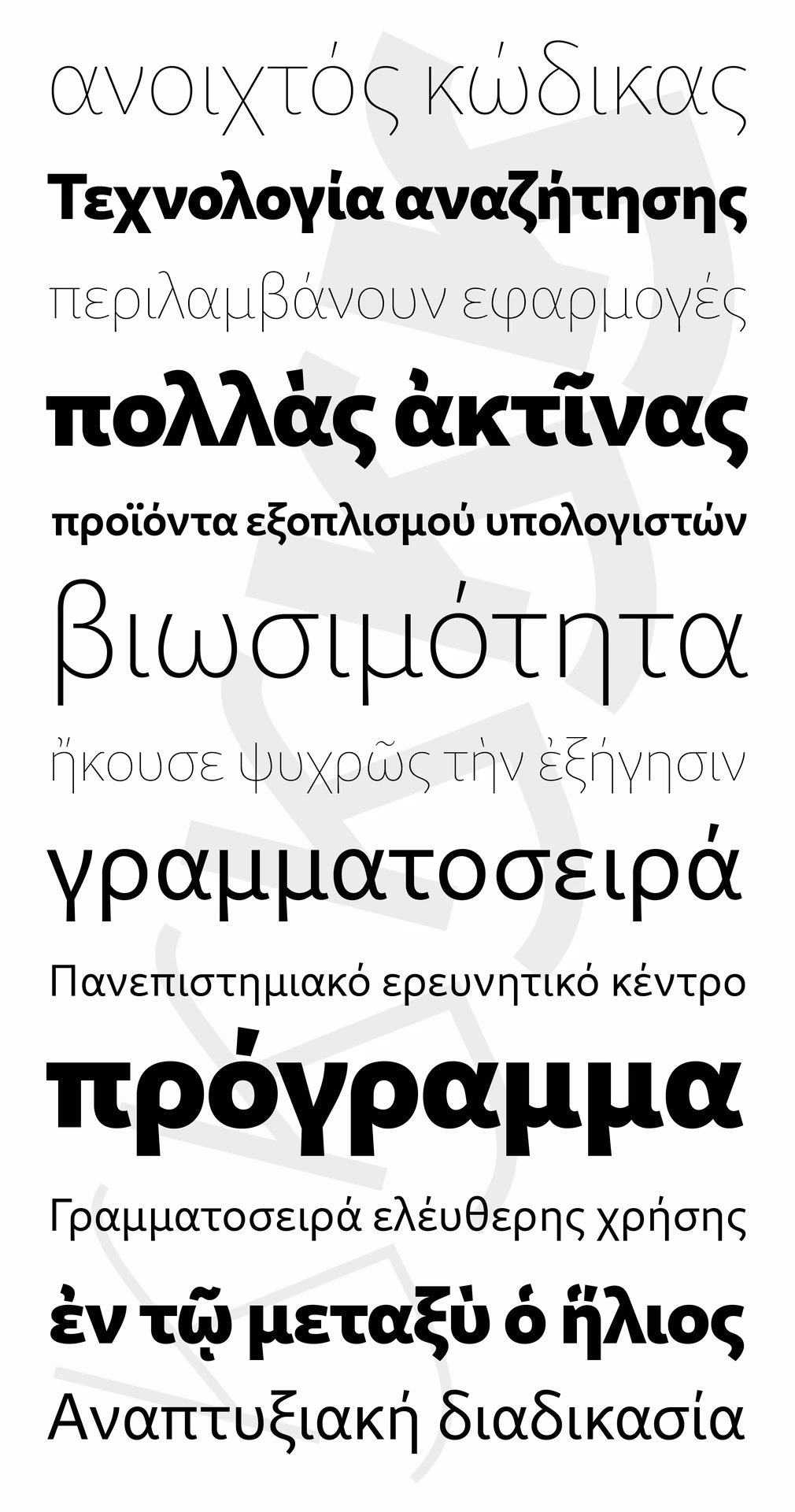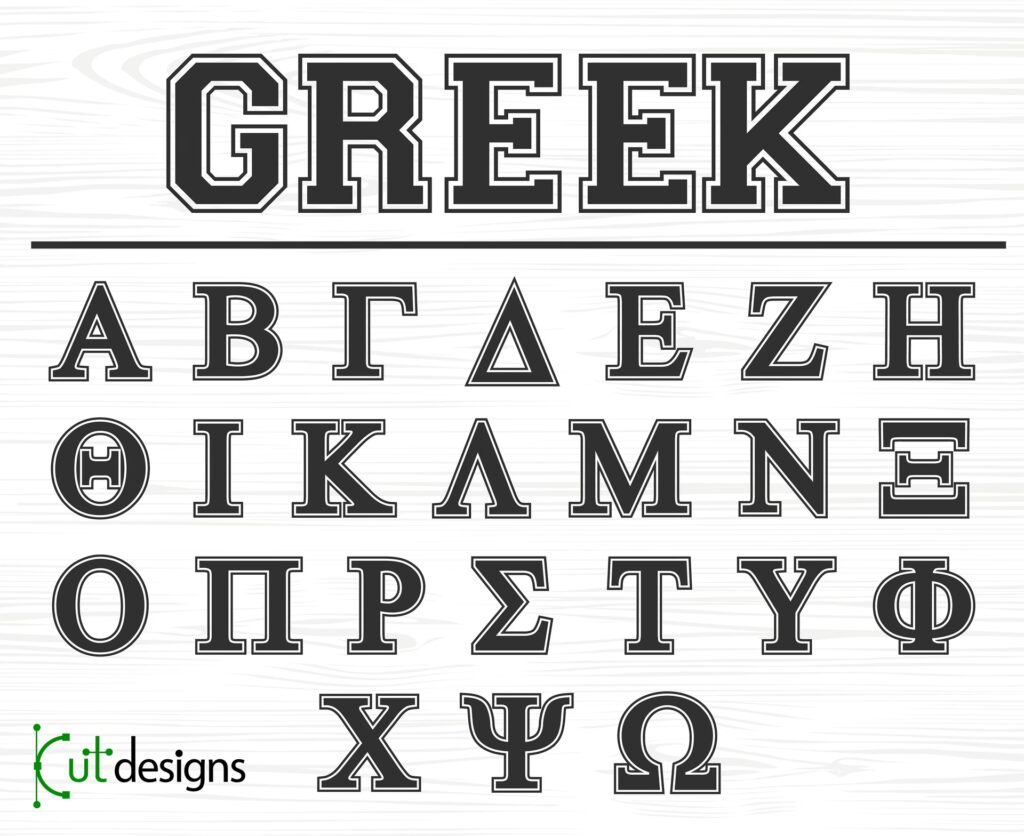
Skriv Græsk: Skrifttyper og Tastaturer
At skrive på græsk på en computer eller anden digital enhed kan virke simpelt ved første øjekast, men især når det gælder oldgræsk med dets mange accenter og diakritiske tegn, kræver det de rette værktøjer. Standardindstillingerne på din computer er sjældent tilstrækkelige. For at mestre digital græsk-skrivning, uanset om du arbejder med klassiske tekster eller moderne kommunikation, skal du typisk bruge to hovedkomponenter: en passende græsk skrifttype og et tastatur, der er indstillet til at håndtere de græske tegn og deres variationer.
Behovet for specifikke værktøjer opstår, fordi det græske alfabet indeholder tegn, der ikke findes i det latinske alfabet, og især oldgræsk bruger et system af accenter (akut, gravis, cirkumfleks) og vejrtrækninger (spiritus asper, spiritus lenis) samt i sjældnere tilfælde andre symboler og arkaiske bogstaver. Disse kombinationer af bogstaver og diakritiske tegn skal kunne vises korrekt og skrives effektivt.
Hvorfor er standard skrifttyper ikke nok?
Det første og mest fundamentale skridt er at sikre, at du bruger den korrekte type skrifttype. I den digitale tidsalder er standarden for tekstkodning Unicode. Dette er afgørende. Ældre skrifttyper, der ikke er baseret på Unicode, repræsenterede ofte græske tegn som små billeder eller brugte private tegnområder i skrifttypen. Dette betød, at tekst skrevet med en sådan skrifttype kun kunne læses korrekt, hvis modtageren havde præcis den samme skrifttype installeret. Teksten kunne ikke genkendes som græsk af søgemaskiner, skærmlæsere for synshandicappede, eller ved kopiering og indsættelse i andre programmer.
En Unicode-baseret græsk skrifttype koder derimod hvert græsk tegn (og dets kombination med diakritikker) med et unikt nummer, der er anerkendt globalt. Dette sikrer, at din græske tekst kan læses og behandles korrekt af ethvert moderne system, der understøtter Unicode og har en passende skrifttype installeret.
Ud over at være Unicode-kompatibel er det vigtigt at vælge en skrifttype, der understøtter det specifikke sæt af græske tegn, du har brug for. En moderne græsk skrifttype indeholder typisk kun de tegn, der bruges i nutidens græsk (monotonisk system, kun akut accent og diaeresis). Hvis du arbejder med oldgræsk, har du brug for en såkaldt polytonisk skrifttype, der indeholder alle accenter, vejrtrækninger og potentielt arkaiske bogstaver som digamma eller specialisttegn til epigrafik, lingvistik eller papyrologi.
Valg af den rette græske skrifttype
Der findes heldigvis flere gode, gratis Unicode-baserede polytoniske skrifttyper til oldgræsk. Valget afhænger ofte af dine specifikke behov og personlige præference for udseende.
To af de mest anerkendte og udbredte er:
• Gentium: Dette er en elegant og alsidig Unicode-skrifttype, der er designet til at understøtte et bredt udvalg af sprog, herunder oldgræsk. Den grundlæggende version, Gentium Basic, er fremragende til de fleste almindelige formål med oldgræsk, da den indeholder de nødvendige bogstaver, accenter og vejrtrækninger. Dens design er æstetisk tiltalende og letlæseligt.
• New Athena Unicode: Denne skrifttype er måske mindre elegant i sit design end Gentium, men den udmærker sig ved at indeholde et endnu større sæt af specialtegn og mere eksotiske diakritiske tegn. Hvis du arbejder med meget specifikke akademiske discipliner som epigrafik (studiet af inskriptioner), lingvistik eller papyrologi (studiet af papyri), hvor du kan støde på usædvanlige symboler eller tegnkombinationer, er New Athena Unicode ofte det foretrukne valg på grund af dens omfattende tegnudvalg.
For de fleste brugere, der primært skal læse og skrive almindelig oldgræsk tekst (f.eks. klassiske litterære værker), anbefales Gentium (Basic) ofte på grund af dens gode balance mellem æstetik, læsbarhed og tilstrækkelig understøttelse af polytonisk græsk.